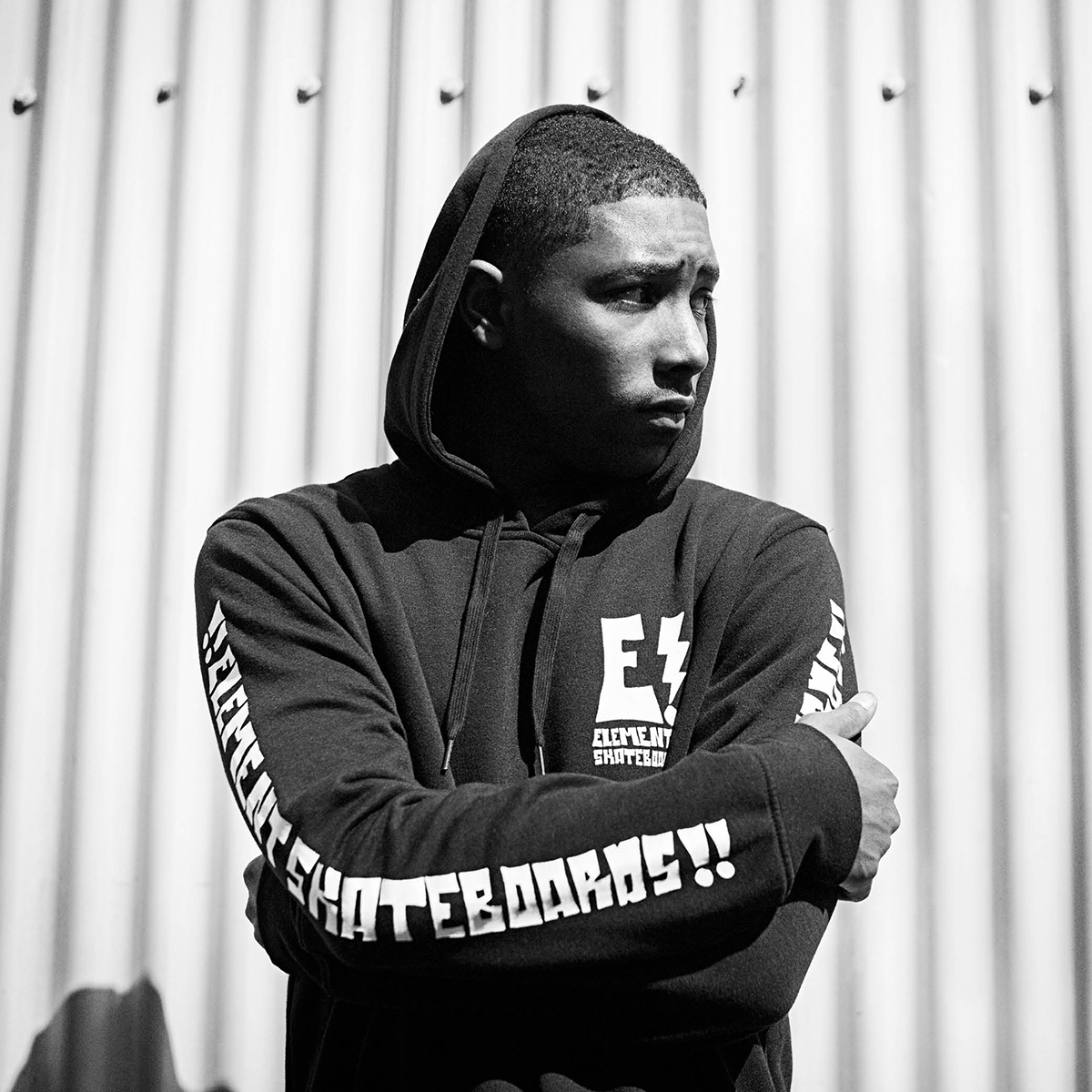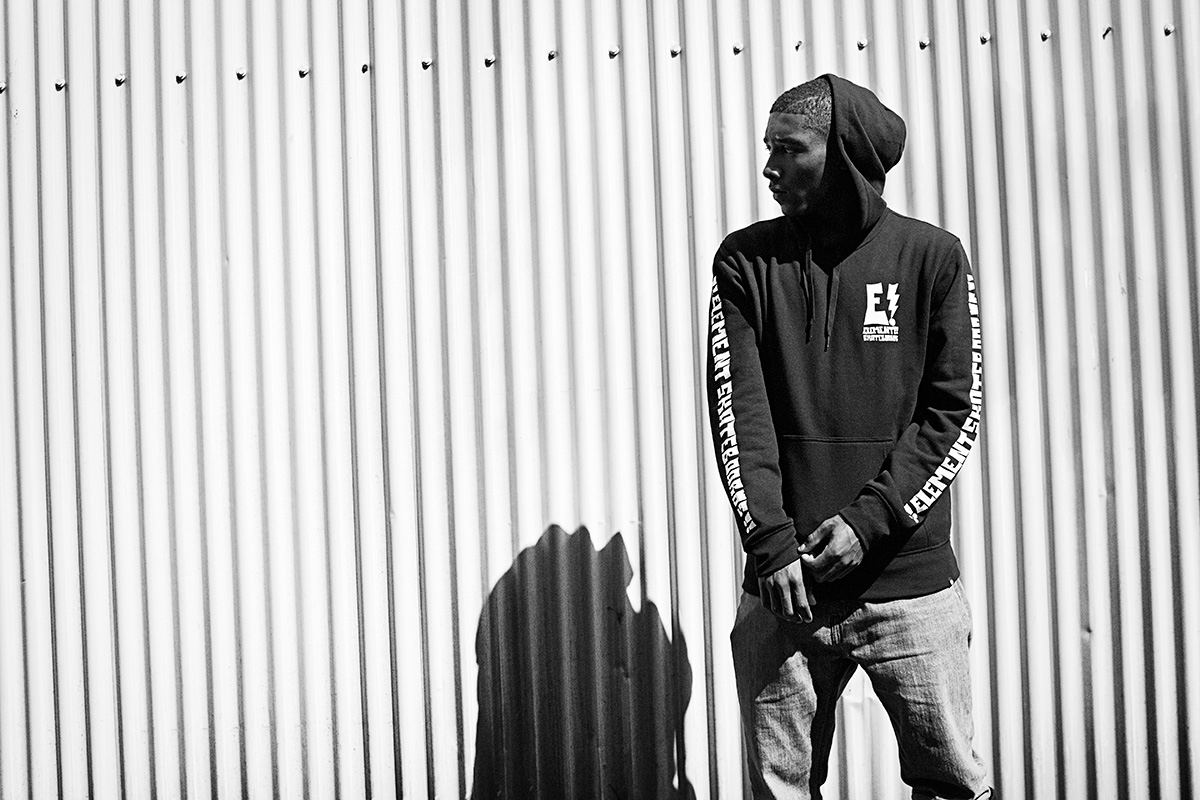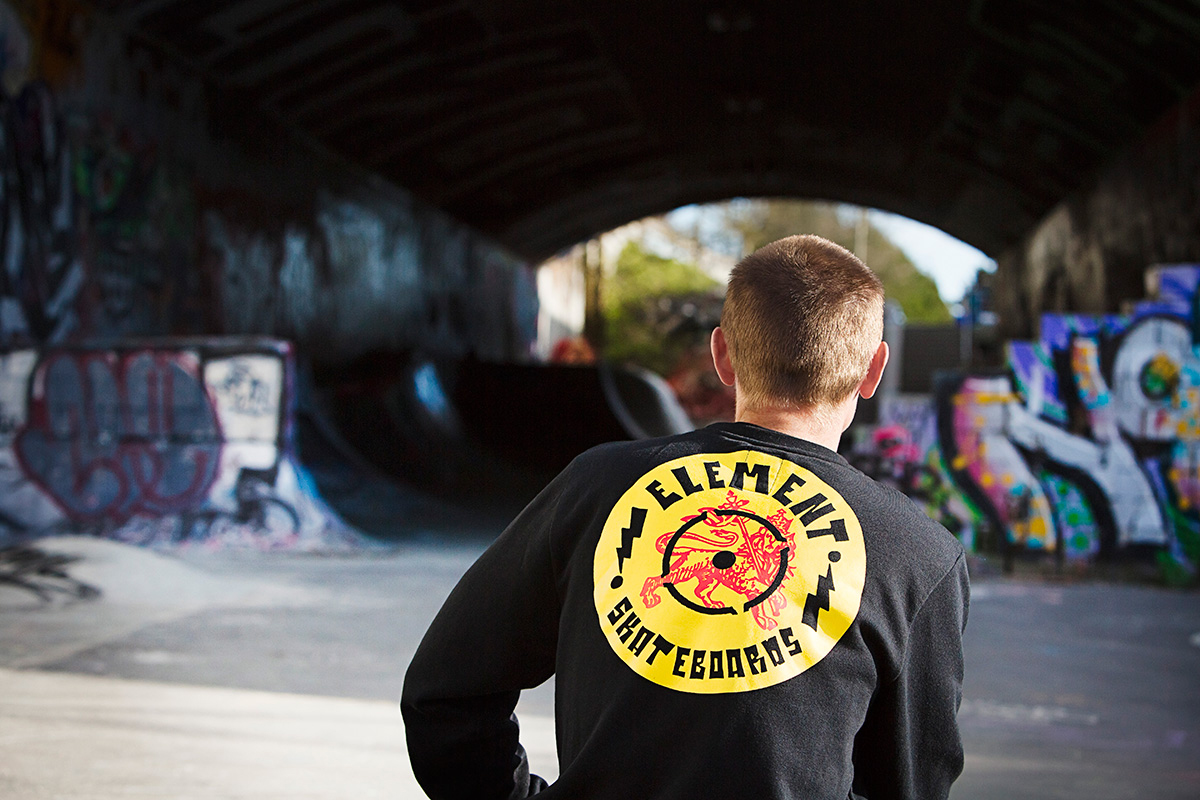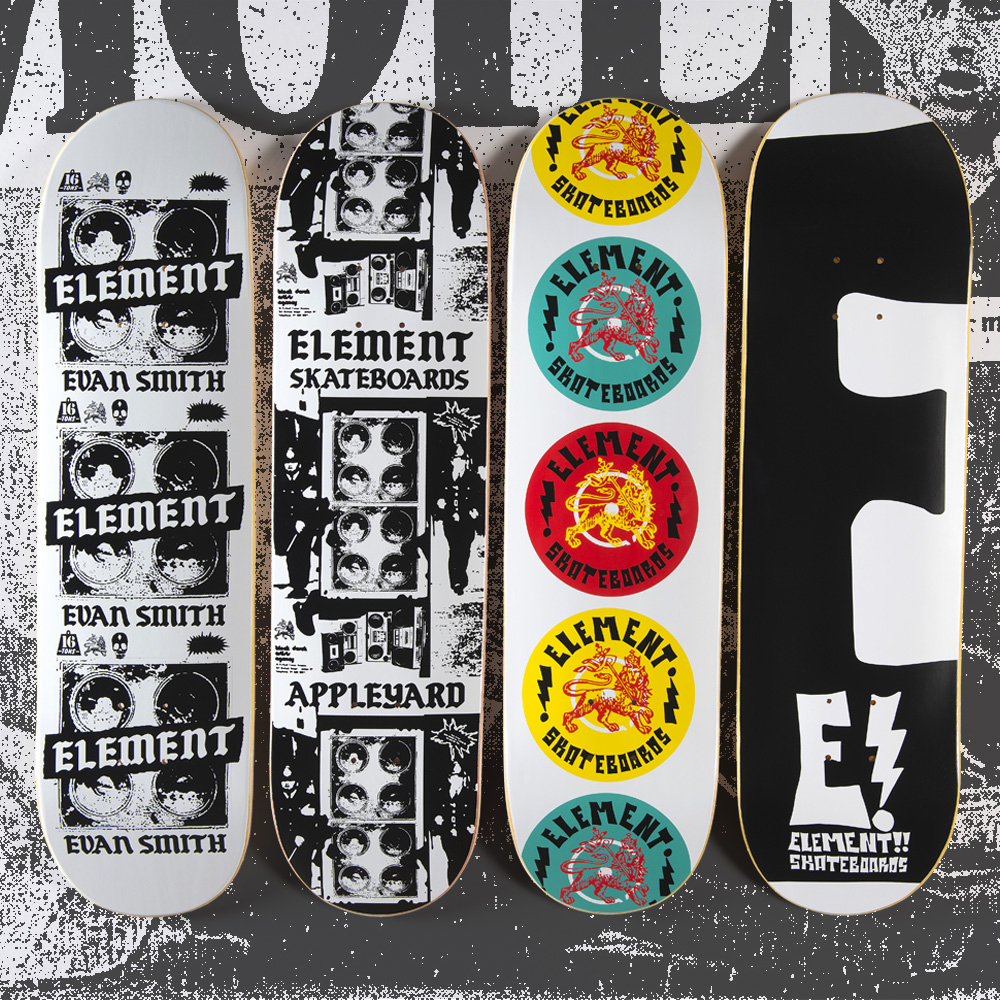
La tipografía está de moda en sudaderas y camisetas. Y cuanto más bizarra sea, mejor. Un ejemplo: La colección Soundsystem de Element
Tipografías góticas, medievales, germánicas, vascas, old english… A día de hoy, cualquier fuente tipográfica con un punto bizarro es la clave del éxito de cualquier sudadera o camiseta. Sobre todo si va impresa en las mangas. La inspiración de esta tendencia puede venir de cualquier lado, pero por lo general viene de la escena underground de todos los tiempos. Sobre todo de aquellos adorables fanzines cuyos titulares estaban hechos a base de recortes tipográficos de lo más variopinto y sorprendente. Todo eso, efecto fotocopia incluido, ha vuelto como por arte de magia. Lo hemos visto en las colecciones de los diseñadores más punteros del momento. También en Element. Pero la marca norteamericana desarrolla la tendencia de una forma mucho más personal: observando sobre todo el dress code del la escena de la música underground de Londres. Mucho negro, golpes fuerte de color, tipografías góticas y bizarras, efectos fotocopia, impresiones en las mangas (esto es un imprescindible en cualquier sudadera que se precie en 2016, que lo sepas). Hay algo de subversivo y reivindicativo en todo ello, no sé muy lo que es, pero me gusta.